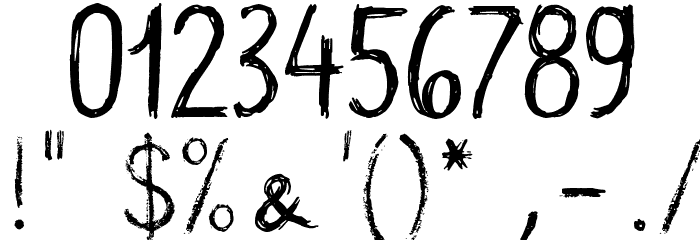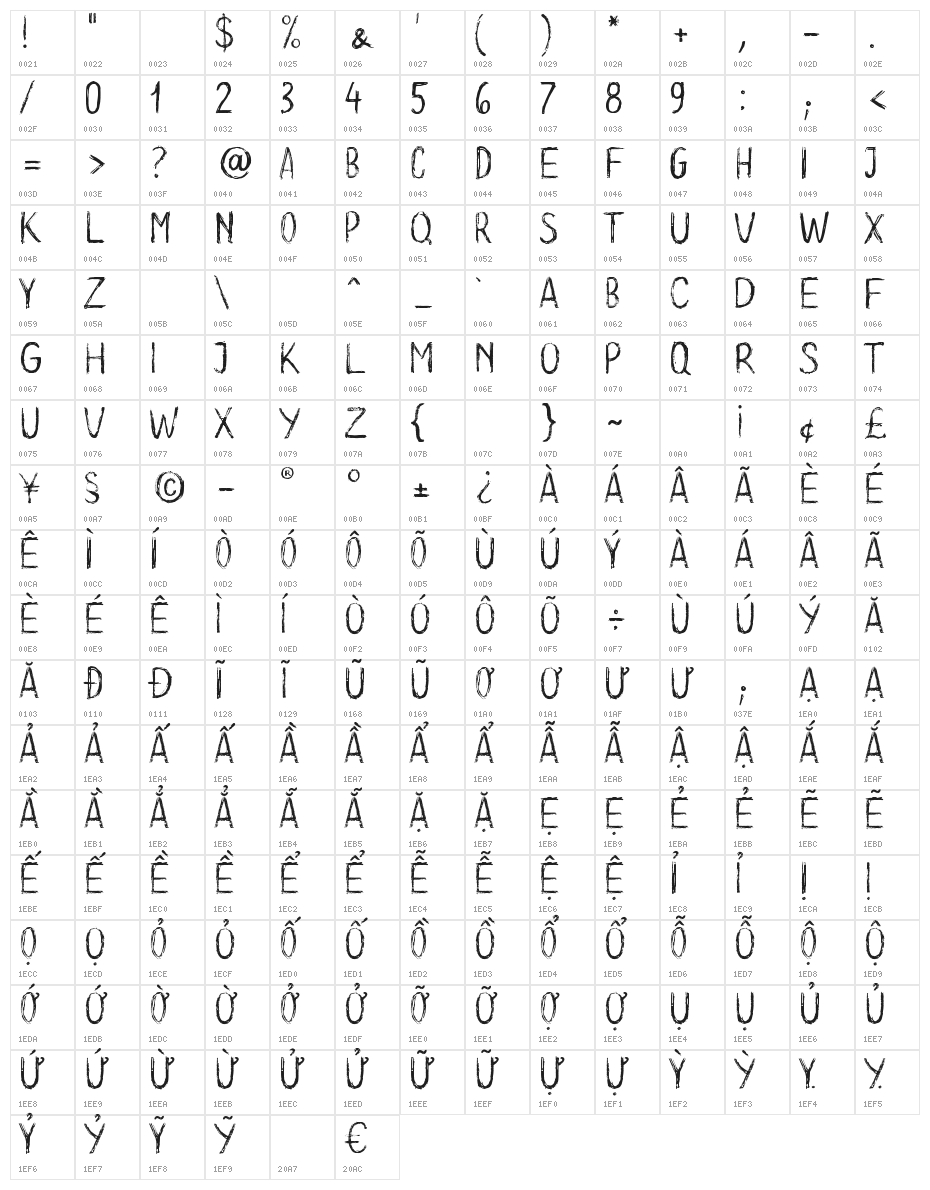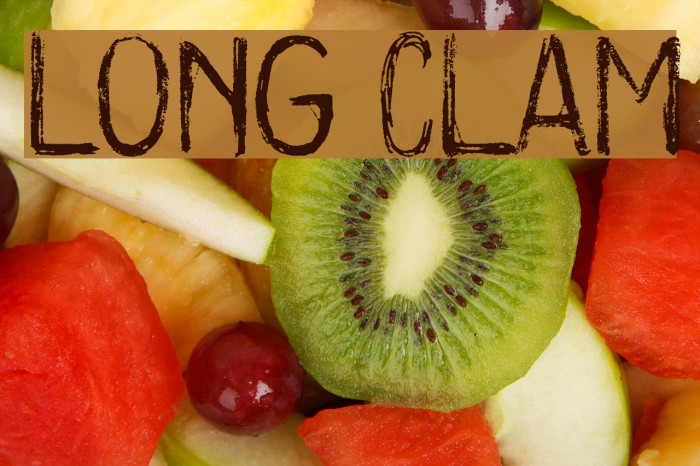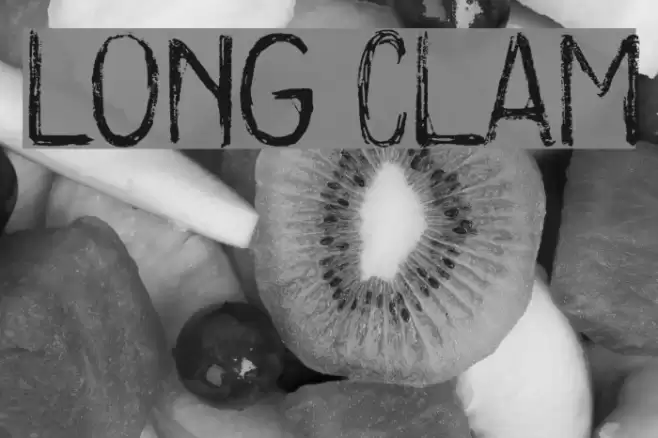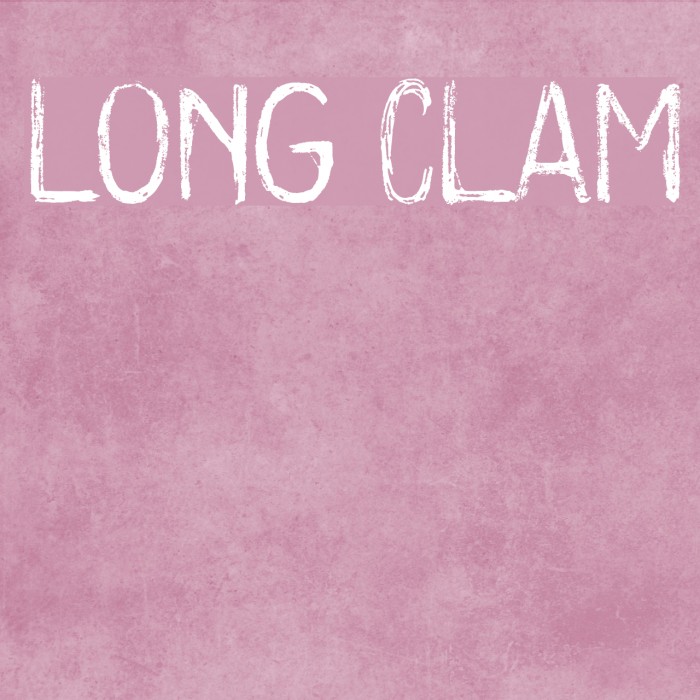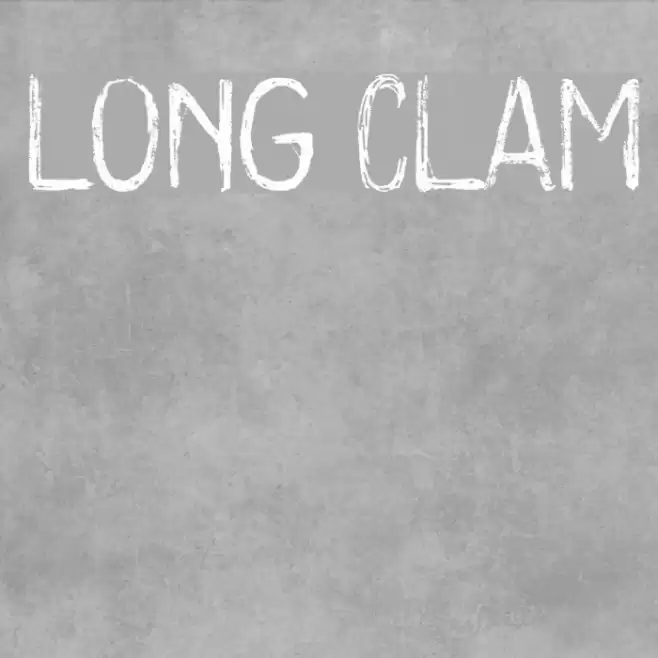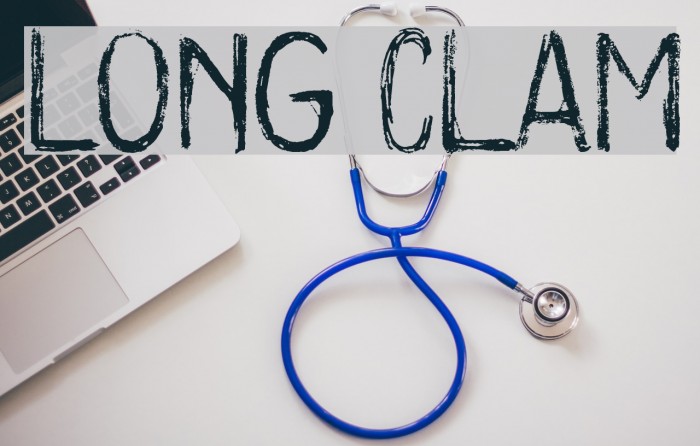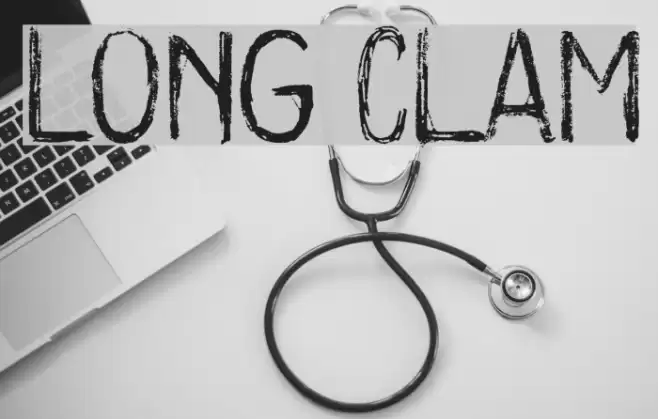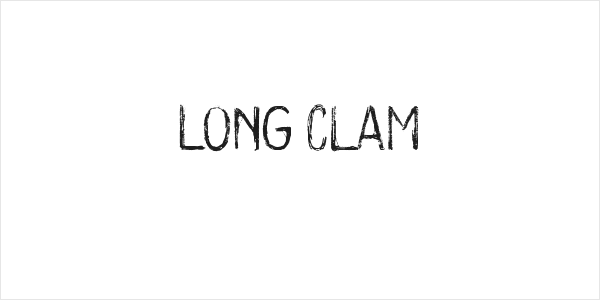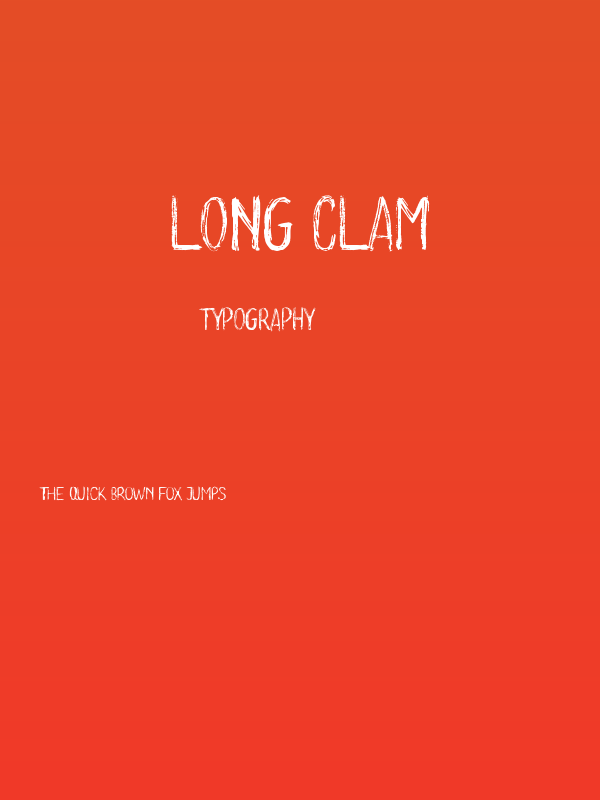
Long Clam Font
| Cas d'utilisation | Headlines, Posters, Branding |
| Projets proposés | Ideal for artistic projects, posters, album covers, and branding that require a bold, expressive touch. |